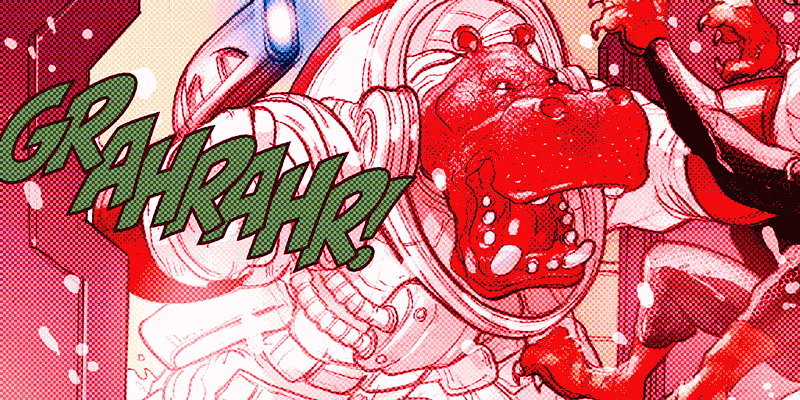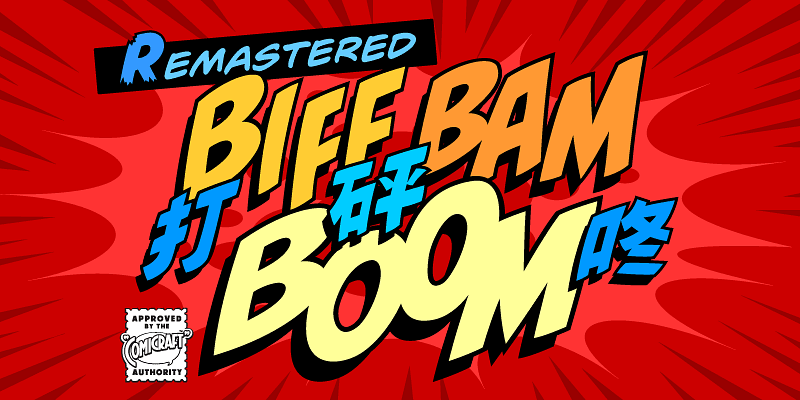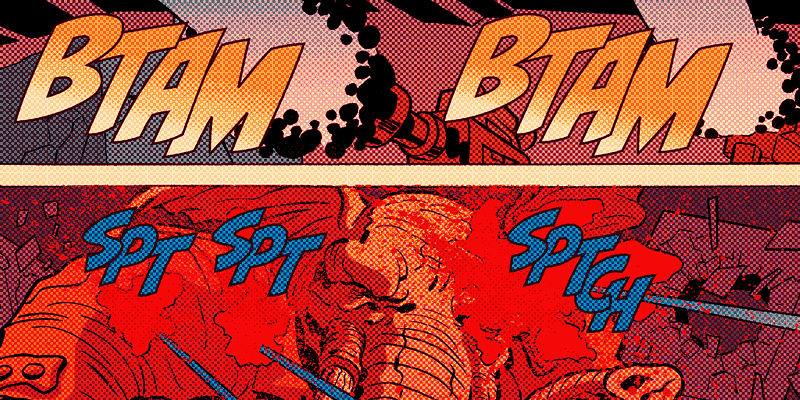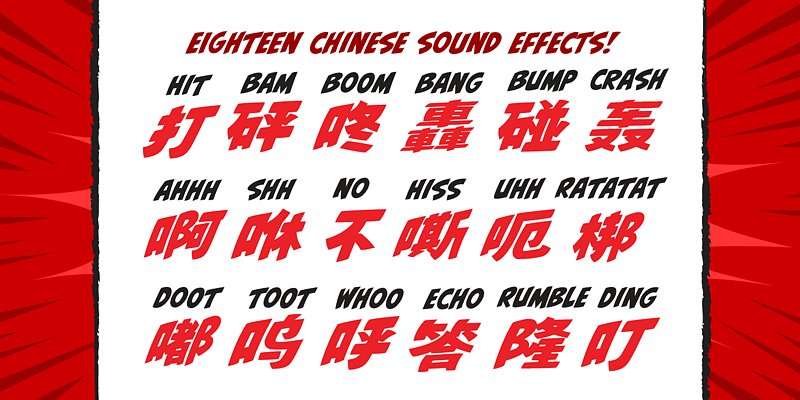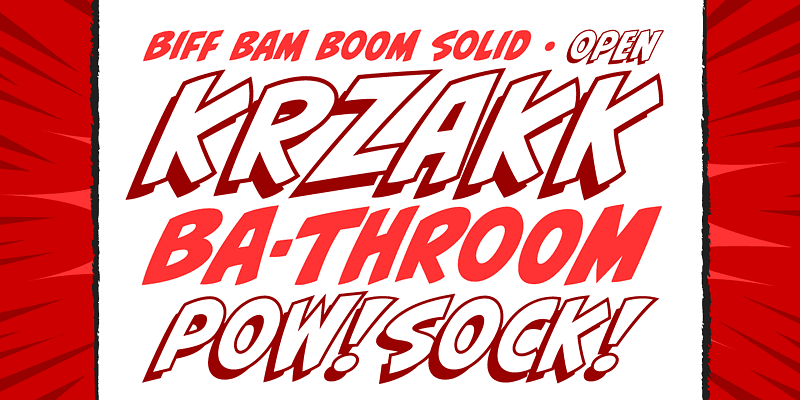
Sacada directamente de las páginas de los cómics de Spider-Man, Daredevil y Hulk, ¡llega BIFF BAM BOOM! Inspirada en el estilo de tipografía legendario de la edad de plata de los cómics, esta es una fuente con fuerte pegada que te dejaría en el suelo con la nariz rota.
¡Los mejores tipos de letra para cómics del mundo! Después de haber dedicado cuerpo y alma para crear diferentes estilos de letra para miles de cómics, las Fearless Fonts de Comicraft irrumpen como la solución revolucionaria para videojuegos, series de televisión, títulos de películas y allá donde se necesiten unas fuentes animadas y divertidas.
En 1992, la pareja de talentos formado por Richard Starkings y John Roshell, junto con el equipo Fearless Fleet of Font Finaglers, empezó su andadura incorporando diseños únicos y tipografías de calidad al mundo de los cómics, la televisión y los videojuegos. Hoy en día son ampliamente conocidos por ser pioneros en el arte de la rotulación para cómics por ordenador.